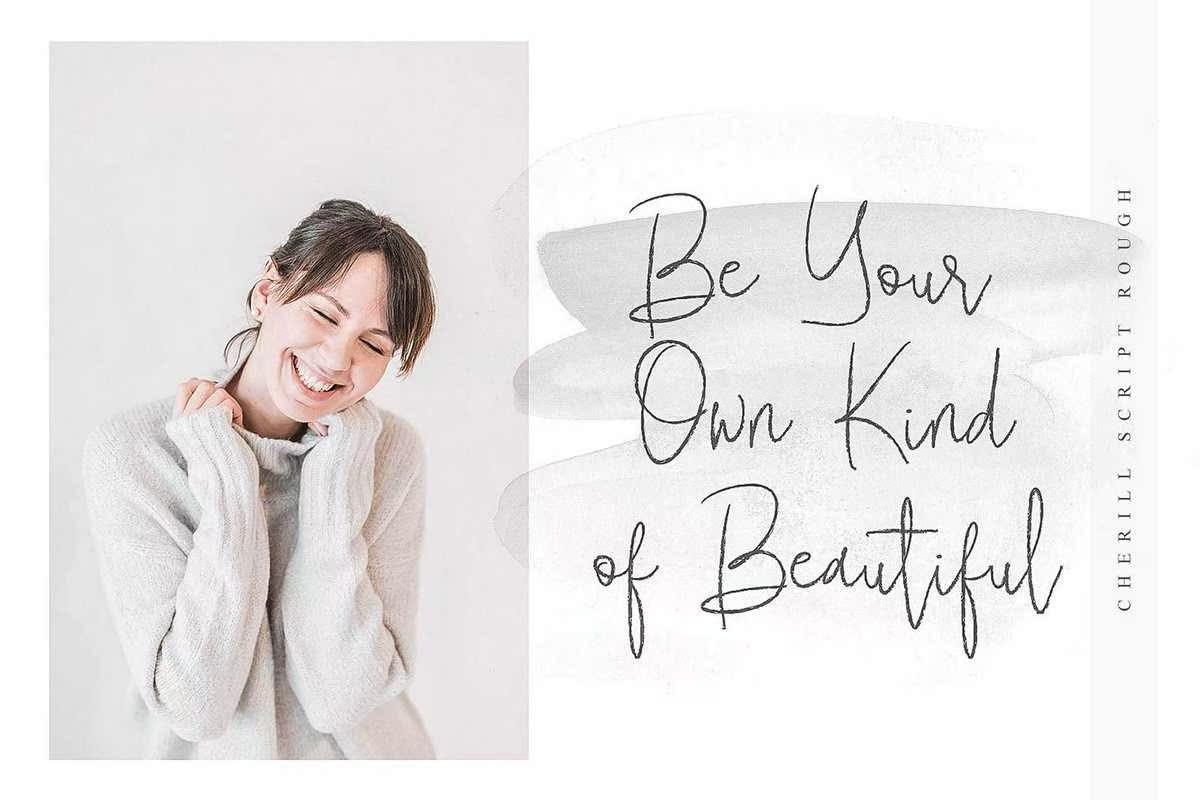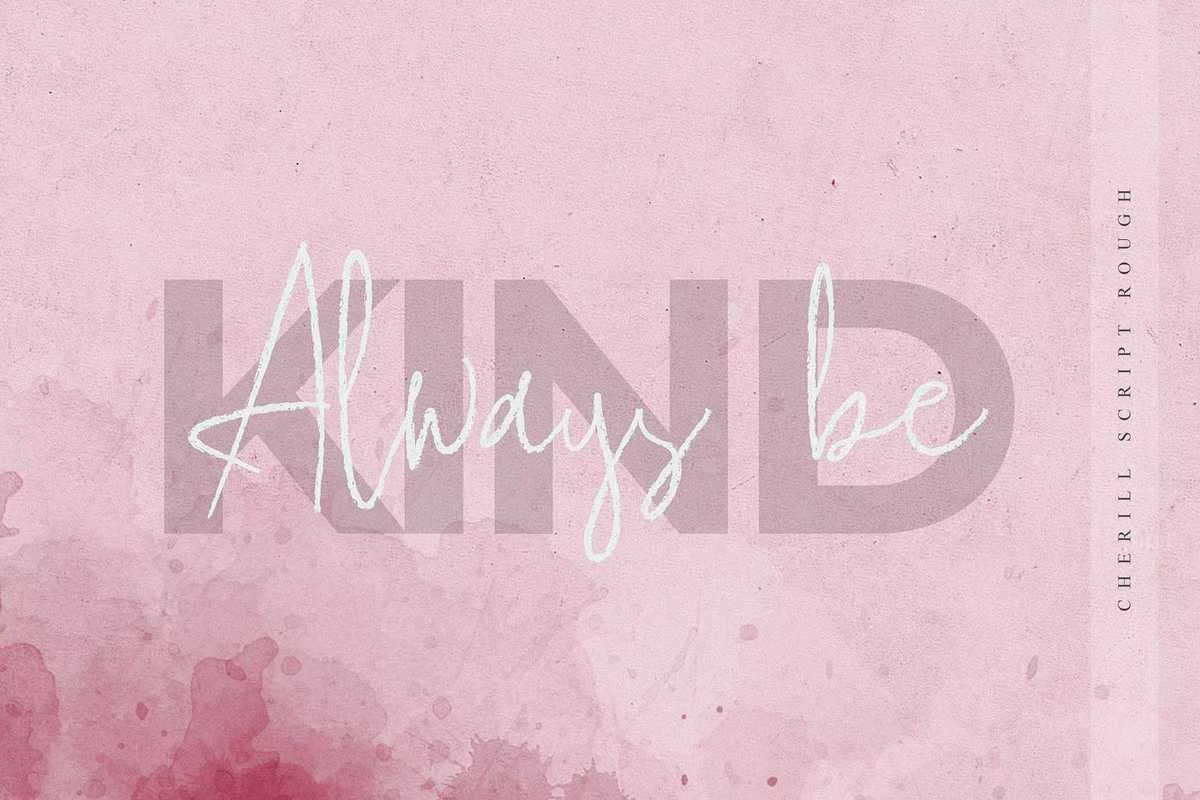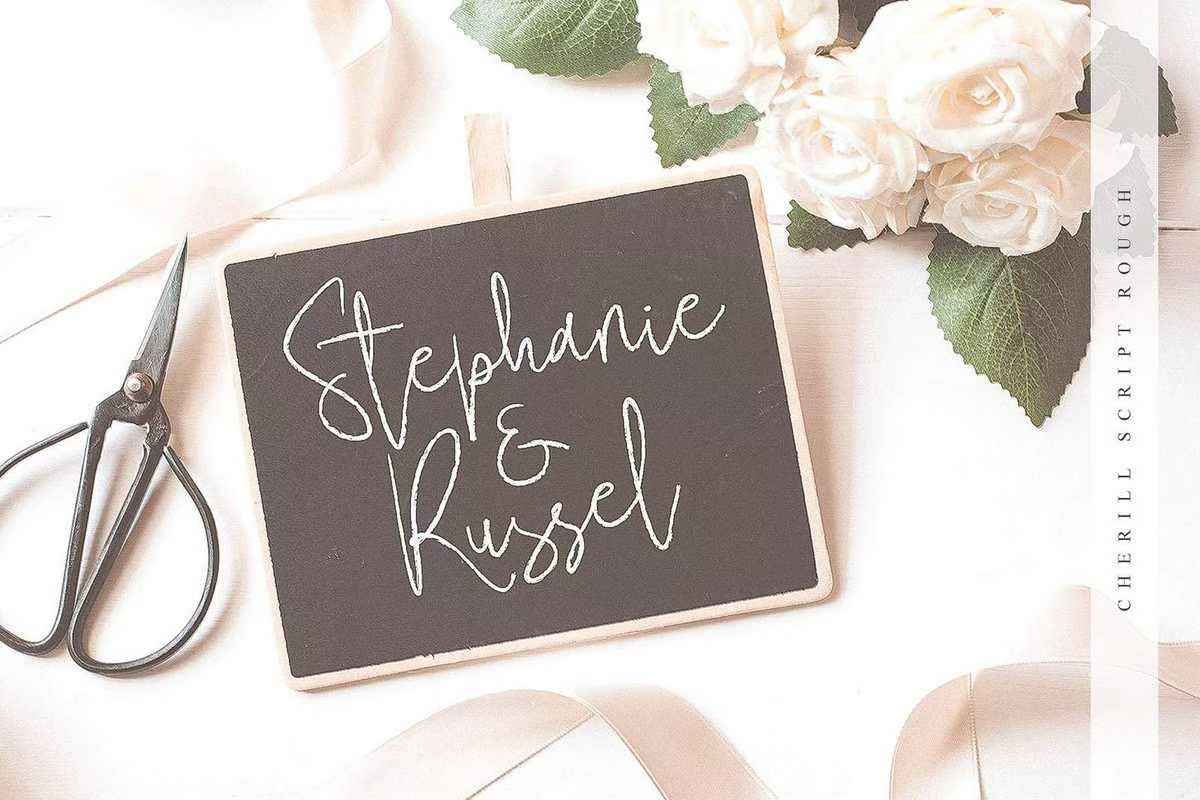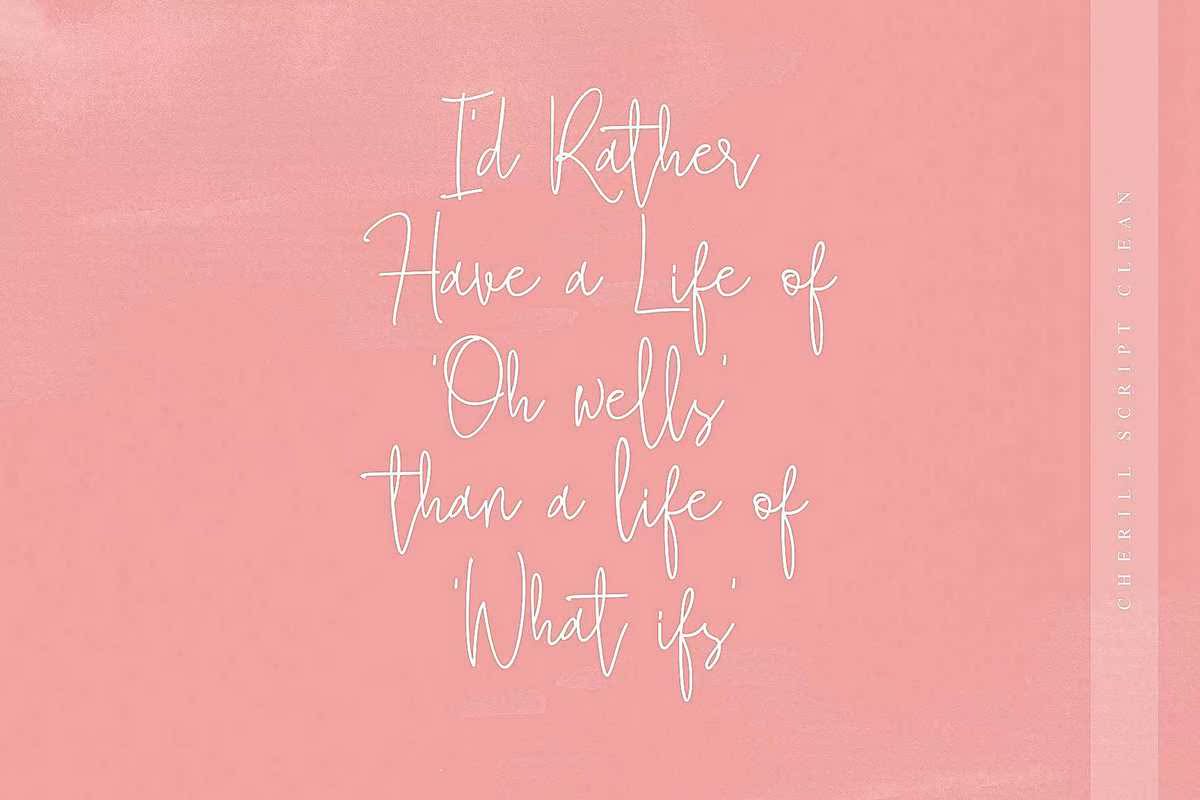
CherillisScript Font具有粗略和干净的版本。它允许YouTurCreateStuningandEasy Handle Instant.IdealForeGo、报价、婚礼、产品标签/包装、时尚、信函、广告、邀请、海报、商品、问候卡等具有粗略和干净版本的CherillisScript Font。它允许YouTurCreateStuningandEasy Handle Instant.IdealForeGo,报价、婚礼、产品标签/包装、时尚、信函、广告、邀请函、海报、商品、问候卡等